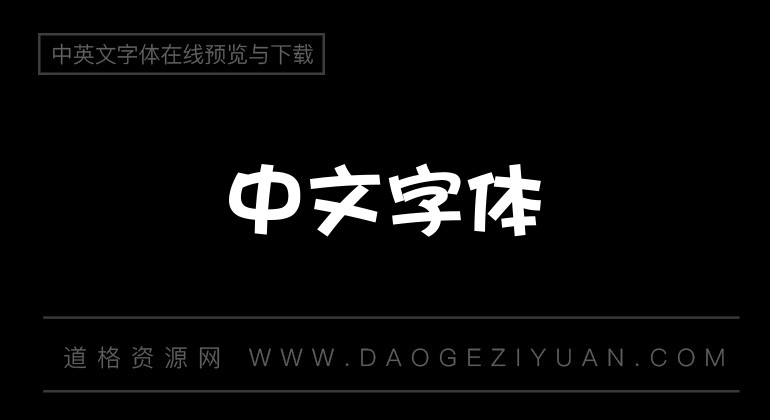
华康海报体W9-B5是一款非常流行的汉字字体,由华康设计,拥有粗细双重设计,可以满足不同的设计需求。字体笔画粗细均衡,笔画细腻,比例合理,且带有一定的空间感,可以使文字更加立体,显示出更加精致的质感。字体的设计简洁大方,给人以清新的感觉,适合用于海报、广告等设计中。文件名:HuaKangHaiBaoTiW9-B5-1.ttf
华康海报体W9-B5是一款非常不错的手写艺术字体,具有很好的视觉感,适合于文化类的宣传设计、商业类品牌的广告和产品包装设计以及个性化文字排版等较多场景。